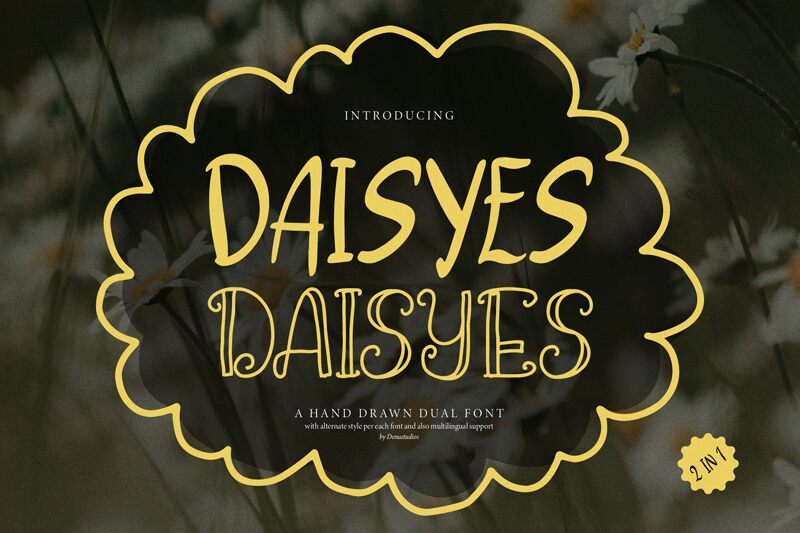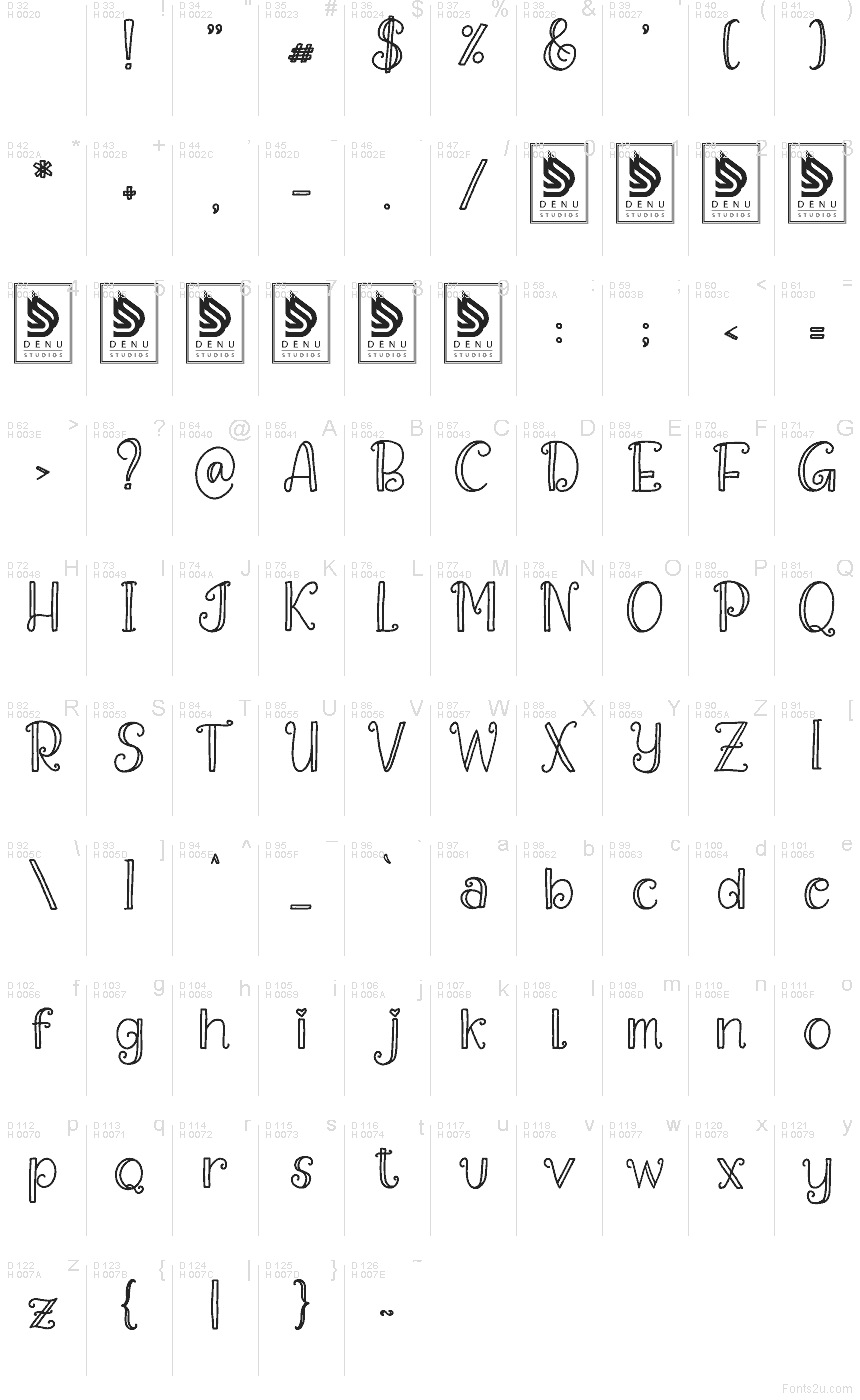
Daisyes Outline de Denustudios est une police de caractères manuscrite en contour, à l'esprit ludique et féerique. Les lettres jouent sur des formes hautes et aérées, avec des traits en boucle et un petit détail en forme de cœur qui confèrent à l'ensemble un aspect léger, amical, comme dessiné à la main.
Elle s'intègre naturellement aux couvertures de livres pour enfants, à l'identité visuelle de cafés, aux cartes de vœux, aux titres de scrapbooking et aux titres de réseaux sociaux où une police avec autant de dynamisme peut porter le ton à elle seule. Utilisez-la pour des noms courts sur des emballages, des lignes d'affiches ou des titres d'invitations lorsque vous recherchez une fantaisie douce sans passer à une écriture manuscrite complète.